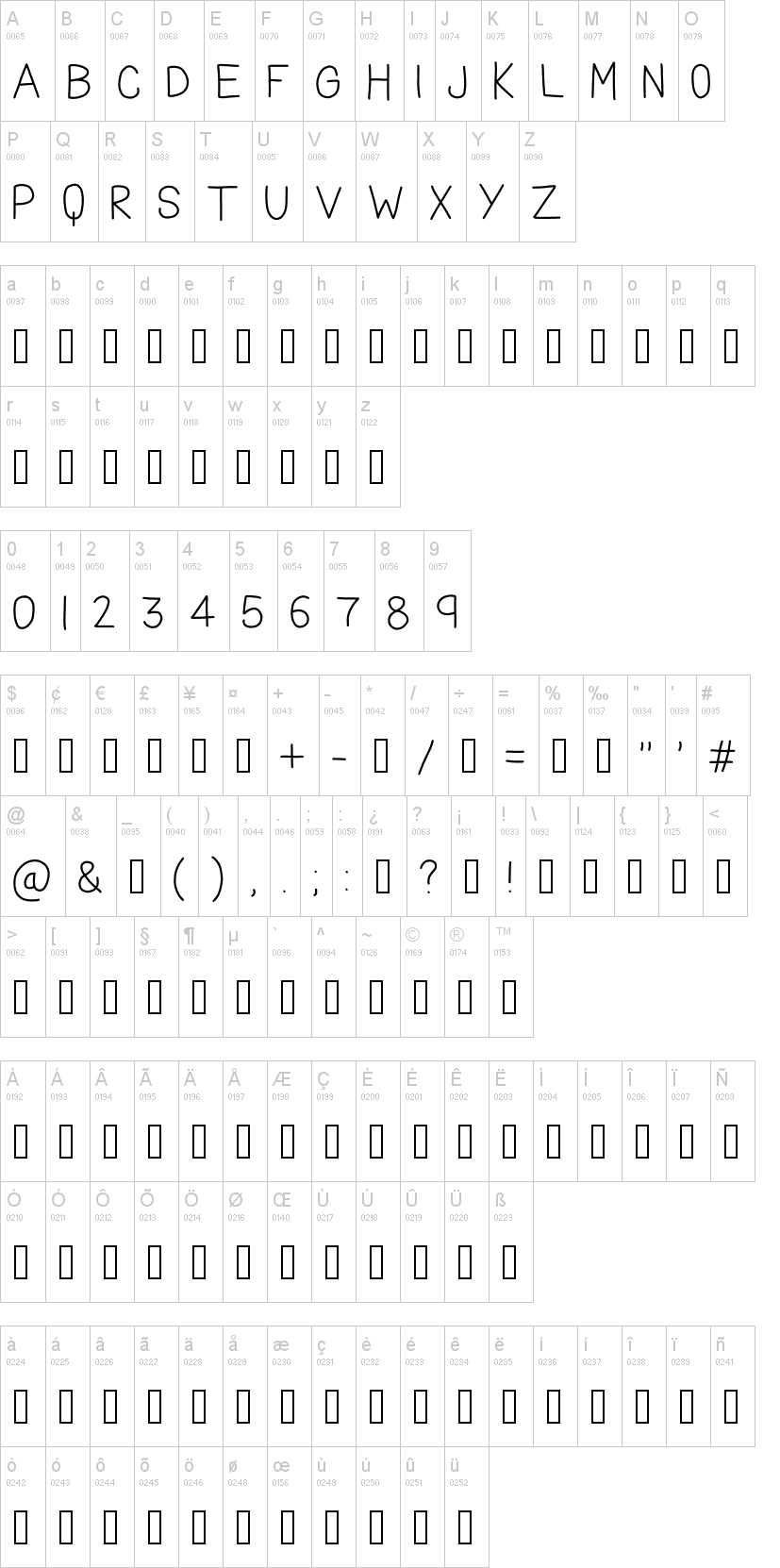
The Friendly Indians
The Friendly Indians 字体是一个友好的、有趣的、手绘风格的字体。它具有独特的笔触和温暖的色调,能够提供一种充满活力的、自然的视觉效果。它的特点是粗犷的线条,曲线和自然的细节,使用这种字体可以给印刷品和网页设计提供一种独特的、有趣的视觉体验。它也可以用于标题、标签、图标和其他文本元素,以及用于品牌标识和商标设计的文字。
The Friendly Indians是一款非常不错的手写艺术字体,具有很好的视觉感,适合于文化类的宣传设计、商业类品牌的广告和产品包装设计以及个性化文字排版等较多场景。